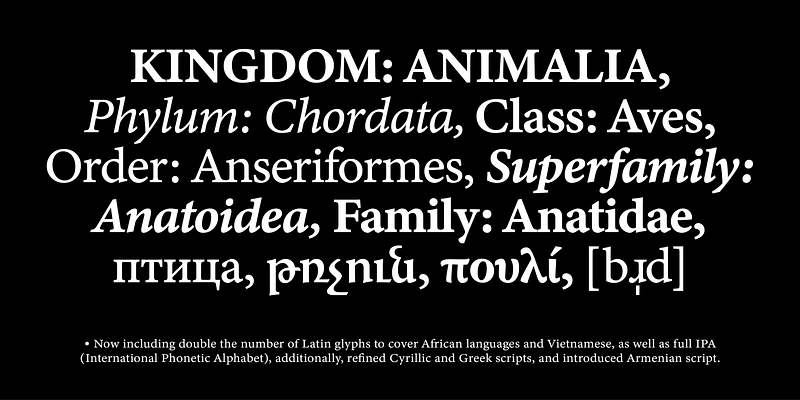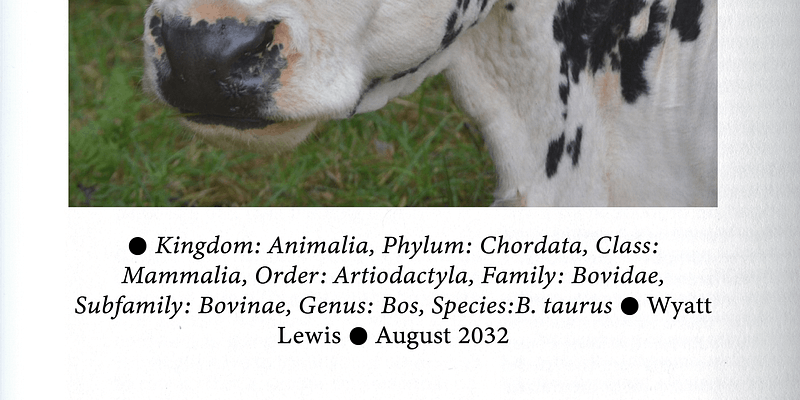
Minion ist eine moderne Schriftfamilie, die von Robert Slimbach entworfen und von Adobe Originals herausgegeben wurde. Seit ihrer ersten Veröffentlichung hat sich die Minion als vielseitige Text- und Display-Schrift erwiesen, die häufig in Büchern und im redaktionellen Design verwendet wird, wo Lesbarkeit und Eleganz eine Notwendigkeit sind.
Mit Minion 3 hatte Slimbach die Gelegenheit, die Minion-Familie zu überarbeiten und weiter auszubauen. Die Anzahl der lateinischen Glyphen wurde fast verdoppelt, um afrikanische Sprachen und Vietnamesisch sowie das vollständige IPA (Internationales Phonetisches Alphabet) abzudecken. Slimbach hat auch die kyrillische und die griechische Schrift umfassend verfeinert und zusätzlich die armenische Schrift eingeführt.
Minion 3 ist in vier Strichstärken und vier optischen Größen erhältlich (Display, Caption, Subhead und text), jeweils mit entsprechender Kursivschrift. Unter minion.typekit.com finden Sie eine ausführliche Darstellung der Designgeschichte und der technischen Überlegungen zu dieser neuesten Erweiterung einer der beliebtesten Schriftfamilien von Adobe.
Das Adobe Originals-Programm wurde 1989 als hauseigene Foundry bei Adobe gegründet, um Originalschriften von beispielhafter Designqualität, technischer Treue und ästhetischer Langlebigkeit zu entwickeln.
Heute besteht die Aufgabe des Type-Teams darin, anspruchsvolle und sogar experimentelle Schriften zu entwickeln, die die Möglichkeiten von Design und Technologie ausloten. Die Schriftarten, die als Adobe Originals veröffentlicht werden, sind das Ergebnis jahrelanger Arbeit und Studien und gelten als Industriestandard für den Ehrgeiz und die Qualität ihrer Entwicklung.